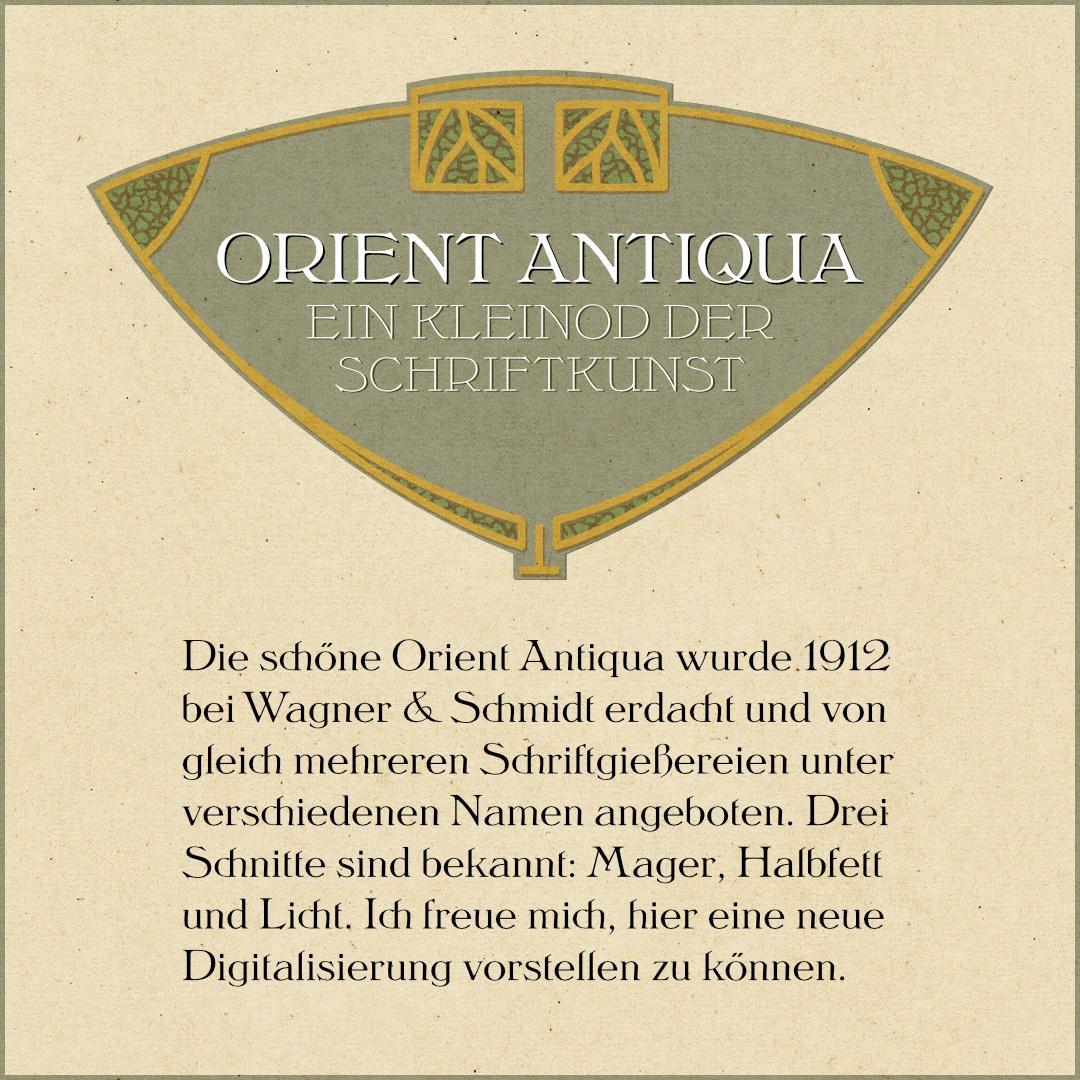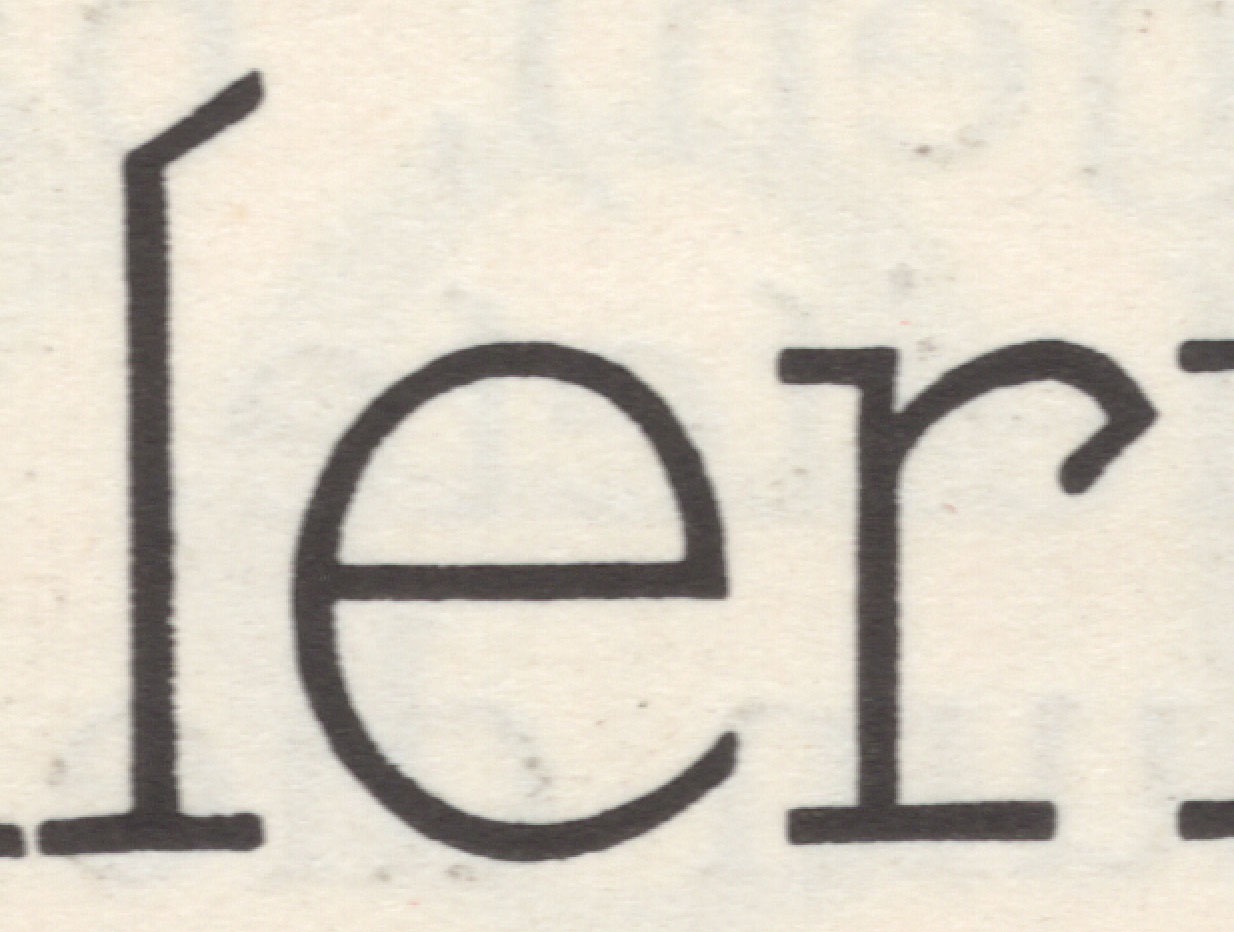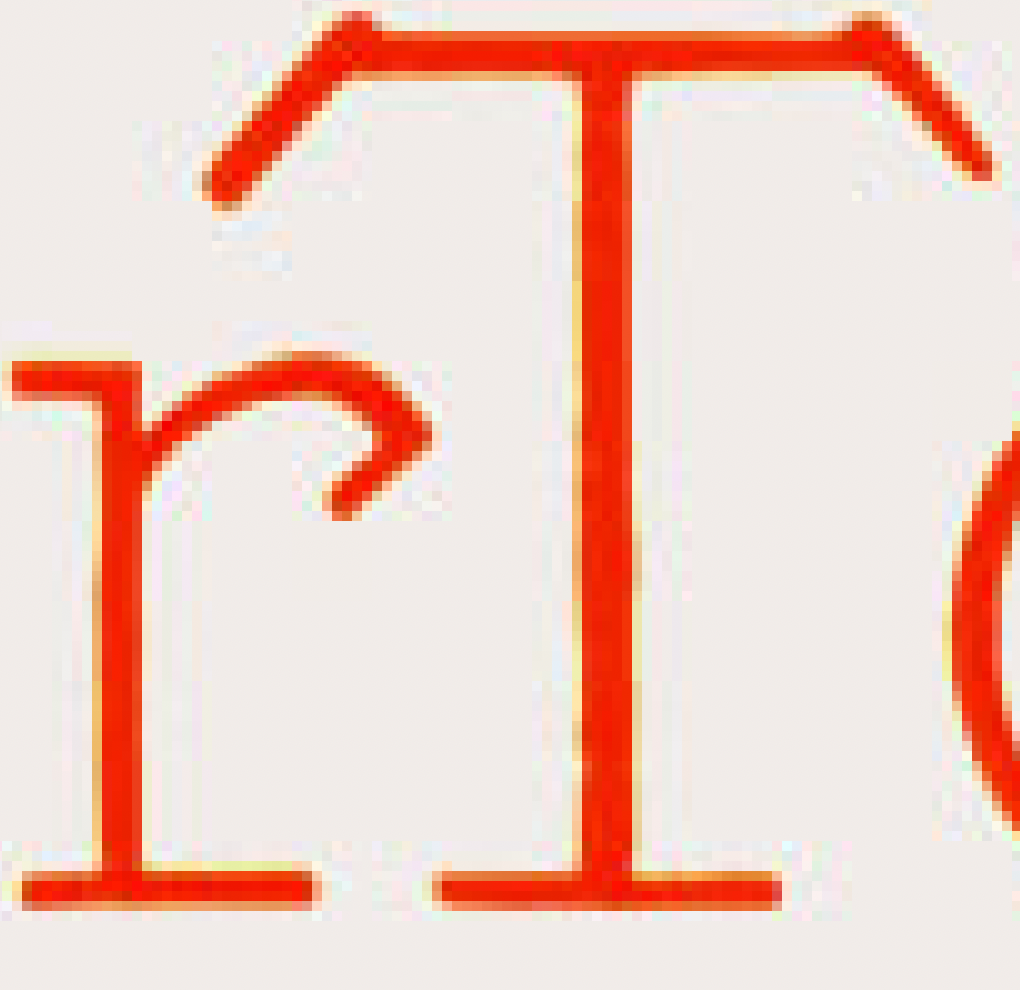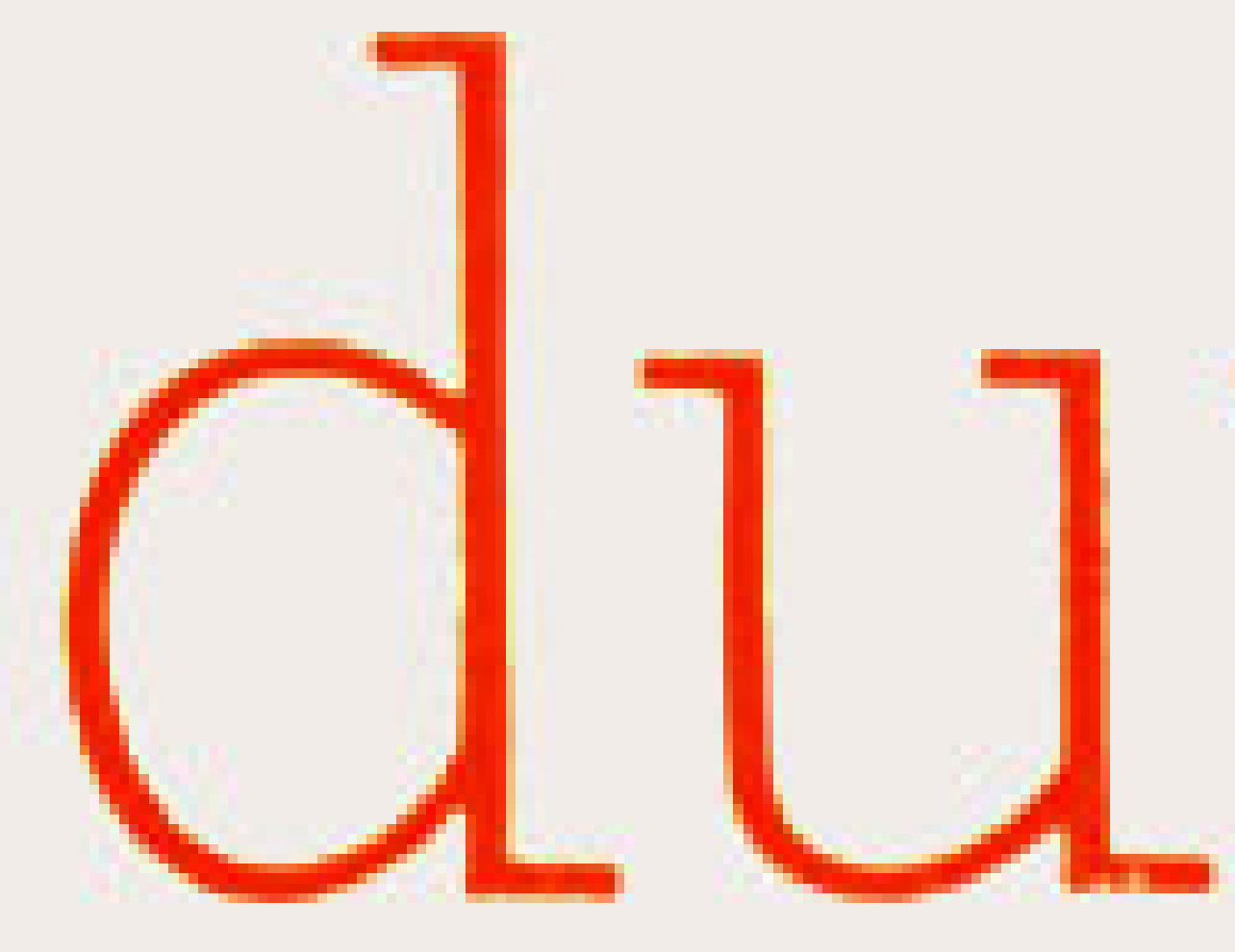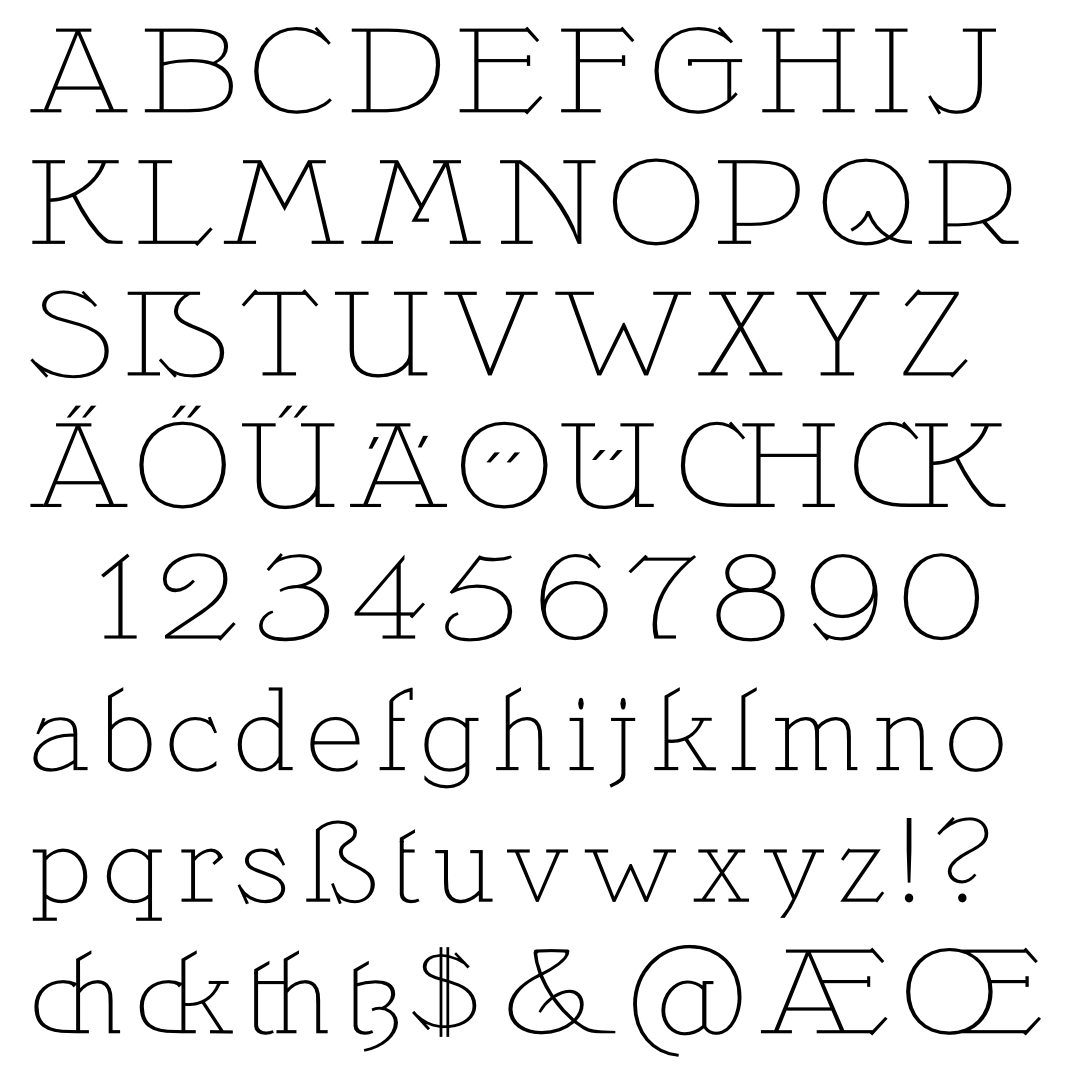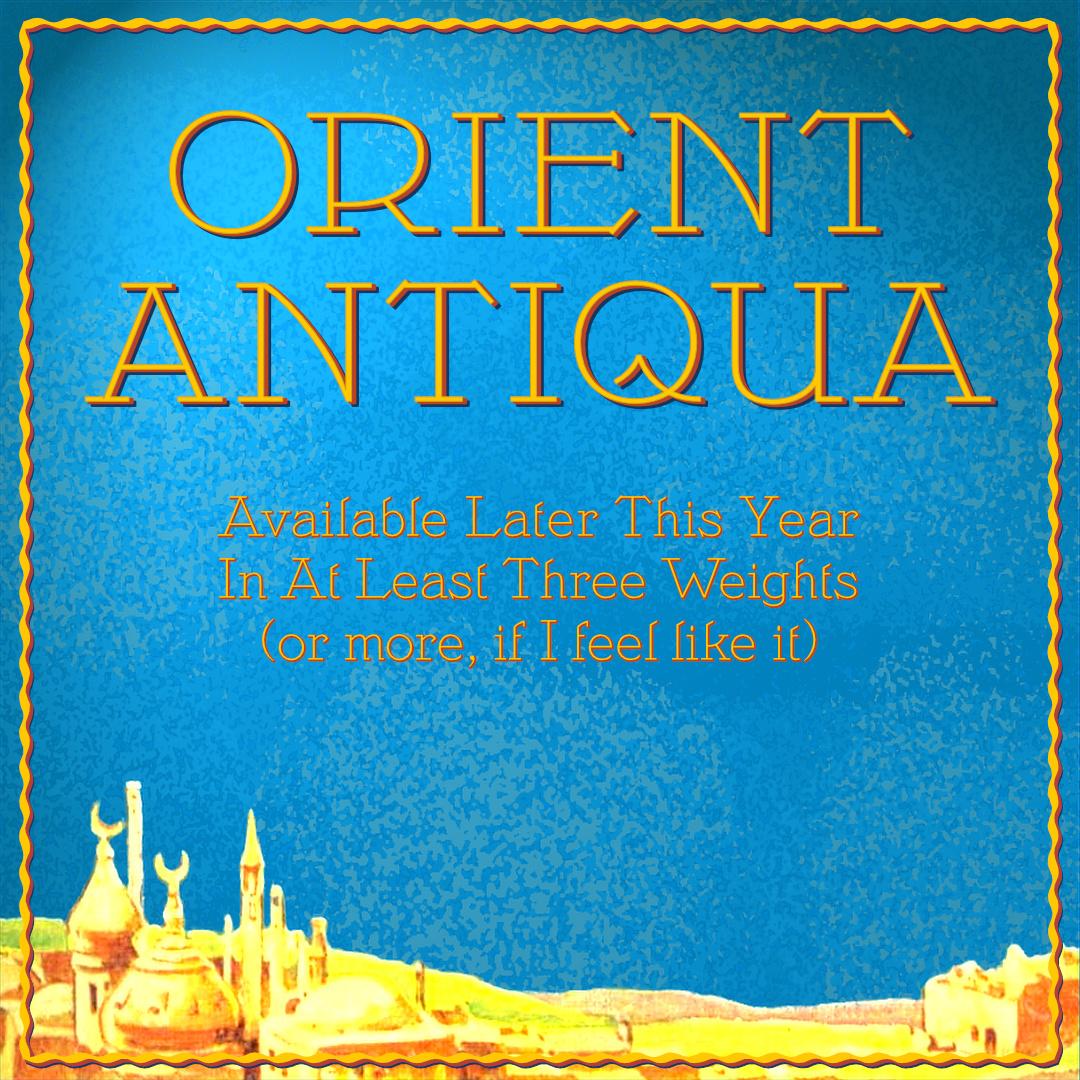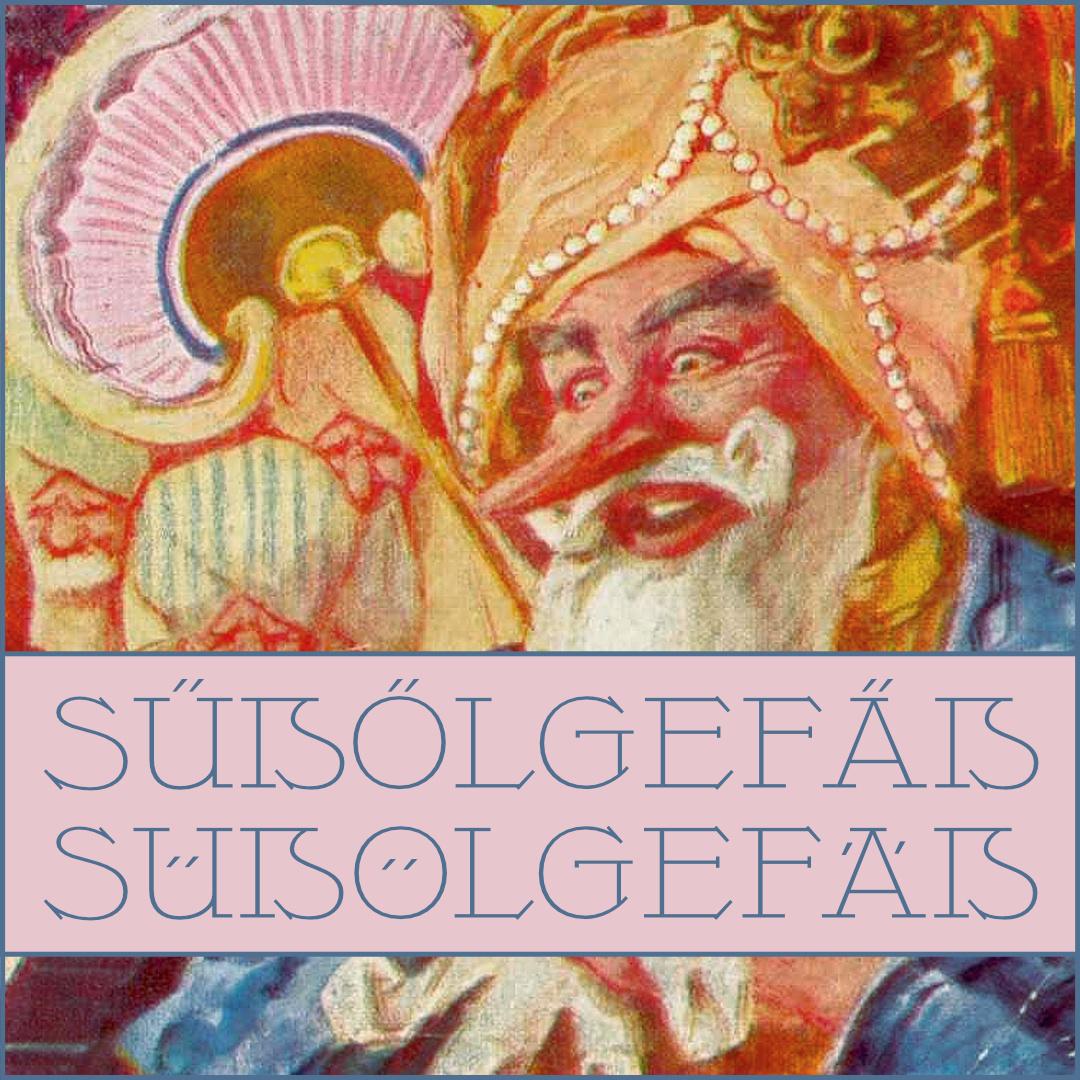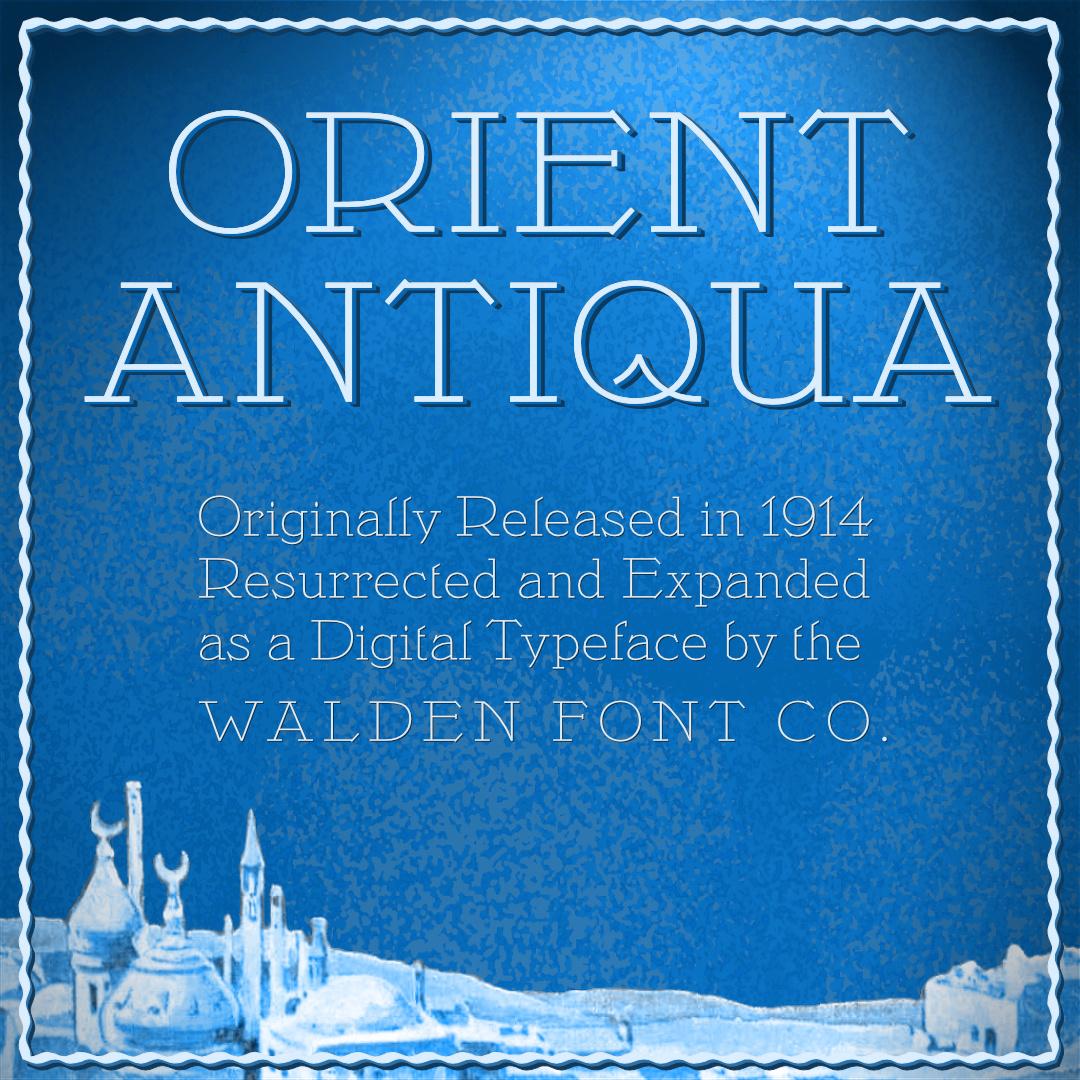
Weihnachtsschriften, die Dritte: Orient Antiqua
Kommt noch. Sie werden länger und schmäler, wie auch schon bei der Mageren. Allerdings scheinen sie auch im Original recht rund zu sein. Überhaupt ist die original-Lichte recht geometrisch gehalten. Das ist für mich mit dem Schnabelschuhorientalismus der Mageren eigentlich nicht zu vereinbaren.
Hier eine kleine Anwendung (Deutsch und Englisch),  und weiter unten der jetzige Stand der Großbuchstaben (als PDF). Ich mache jetzt erstmal die Gemeinen, aber jedesmal wenn mein Blick auf die Großen fällt, finde ich wieder einen neuen Mangel 🙄
Lichte Großbuchstaben:
Nun also weiter mit der Orient Antiqua. Nach der langen Pause gefiel mir die Lichte version ganz und gar nicht. Die Gemeinen sind grob und ungleichmäßig, und besonders die runden Serifen passen nicht. In der – vorher übersehenen – Probe sind die Serifen eindeutig eckig:
Die Schrägen aber nicht?? Leider werde ich aus diesem niedrigauflösenden Bild nicht richtig schlau. Hat jemand da vielleicht etwas Originales?
Ich habe einen kleinen Katalog, in dem die Schrift vorkommt. Die Serifen sind alle leicht abgerundet. Die Schrägen auch. Allerdings ist die Abrundung an den Schrägen nicht immer rechtwinkelig vom Strich. Ich lade gleich ein Bild hoch.
Klasse, vielen Dank, Dan!!! Jetzt gilt es, auszusortieren was gewollt ist, und was ein Artifakt ist. Beim r ist der runde Haken sehr klar.
Da es jetzt hier endgültig zu kalt für Aktivitäten im Freien ist, mache ich hier wieder mit Hochdruck weiter. Mit den Formen der Leichten bin ich jetzt zufrieden. Die Ausrichtung kommt erst noch. Vielleicht gibt es unter Euch das eine oder andere Adlerauge, das mir noch einen Patzer zeigt?
Der Haken beim M ist jetzt spitzwinklig, was mir auf den ersten Blick besser gefiel als vorher. Allerdings kann ich diese Formensprache sonst nirgends finden. Beim Q gibt es eher einen Bogen und beim f ist der Winkel eher abgerundet. Vielleicht noch etwas harmonisieren untereinander?
Die Versal-Umlaute (?) sind mir nicht klar … sind das Umlaute oder sind Ö und Ü die ungarischen mit Doppelakut?
Gibt es einen Grund für den unterschiedlichen Winkel der zweiten drei Umlaute?
Wie mag das € aussehen?
Der gehört kupiert. Hab ich glatt übersehen! Vielen Dank 🙂
Die "normalen" fliegen noch zu tief, und sind auch zu lang. U. U. sollte ich sie vielleicht den i-Tüpfelchen angleichen. Der zweite Satz entspricht den Originalen. Die haben auch unterschiedliche Winkel. Keine Ahnung ob das vom Schöpfer so gewollt war, oder sich irgendwie ergeben hat. Man sieht sie ja nicht nebeneinander.
Bei den Titelsatzumlauten von Ö und Ü aber auch, oder? Die unterschiedlichen Winkel würde ich hier auch harmonisieren. 😉
Ich denke das wäre eine gute Idee! Vielleicht machten diese auch bei ? und ! eine bessere Figur.
Das schon, aber sie kommen in einem Wort vor. Da wäre die unterschiedliche Höhe seltsam.
Das obere Süßölgefäß sieht mir immer noch nach ungarischem Doppelakut aus – sehr schräge Umlaute im Vergleich zu den sehr aufrechten Buchstaben.
ÄÖ wird häufig als Abkürzung für Ätherische Öle verwendet. Da hat man sie dann direkt im Vergleich …